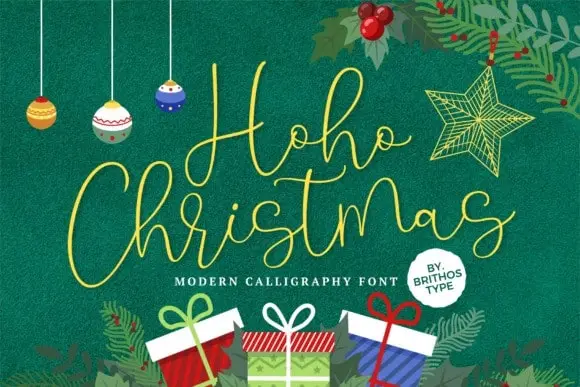
A Hoho Christmas Font é uma elegante e fluida fonte escrita à mão, com um apelo autêntico que transmite a sensação de algo feito pelas próprias mãos. Desenvolvida pelo designer brithostype no 99designs, esta font se destaca por sua aparência delicada mas não enfadonha, e equilibrada entre variadas linhas. Perfeita para os projetos inverno, a Hoho Christmas Font oferece um estilo casual que faz do seu uso uma decisão segura, sem você ter nenhuma dúvida sobre o resultado final. Sua sofisticação e naturalidade tornam essa font ideal para uma variedade de aplicações, incluindo assinaturas em logotipos, postais de aniversário, mídias sociais, cartões de casamento, blogue, headlines e mais. Não importa qual projeto você esteja criando ou quão simples que seja a sua mensagem, a Hoho Christmas Font garante uma apresentação memorável e encantadora para cada elemento de design. Uma vez adicionada ao seu próximo projeto, é garantido que não ficará desapontado com o resultado. A Hoho Christmas Font é uma font perfeita para aqueles amantes da decoração natalina e quem busca um toque autêntico em seus designs digitais.